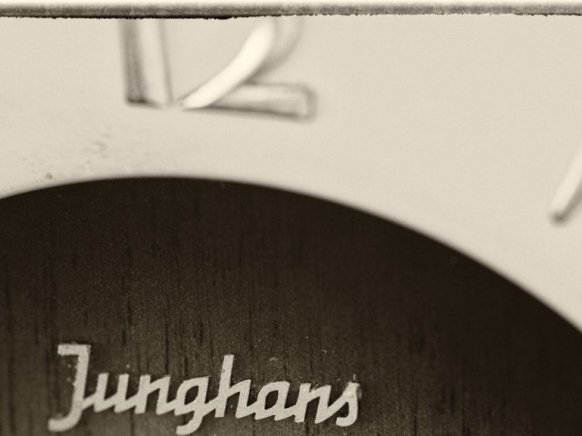
Schrift von alter Junghans Wanduhr
ich durchsuche nun schon seit Tagen das Netz nach dem Schrifttyp dieses alten Logos. Ich bin mir fast sicher die Schrift bereits in einem anderen Kontext gesehen zu haben. Es wäre mir eine große Hilfe wenn jemand hier wüsste, um welche Schrift genau es sich handelt.
Das ist wieder einmal ein Beispiel für ein Logo, dass in einer Zeit entstanden ist, in der sich Grafilker nicht hingesetzt haben, erst einmal stundenlang nach einer passenden Schrift zu suchen, sondern sich ein Blatt Papier und einen Bleistift schnappten, schnell etwas skizzierten, dann das mit dem Kunden besprachen, und gabs für eine Skizze ein OK wurde davon eine Reinzeichnung angefertigt.
Es ist zwar möglich, dass es dann eine ähnlichre Schrift heute gibt, aber oft war dann nicht die Schrift Vorbild fürs Logo, sondern eher das Logo Vorbild für die Schrift.